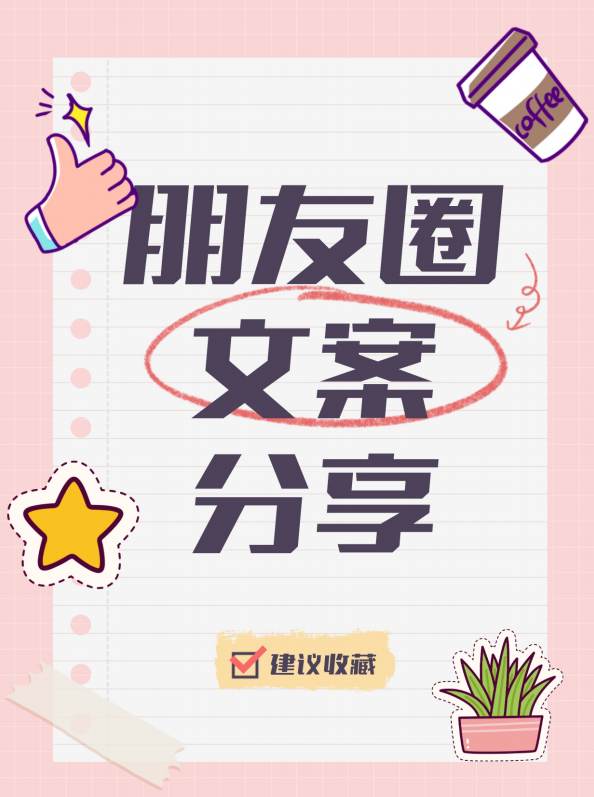
高手庆科冷酷体 大黑
Master-ZqklengkuGB Bold
该字体是一款宽扁的直线黑体,整体硬朗倾斜,中宫略大,布白均匀,重心统一。笔画设计无过多装饰,笔形简约,横细竖粗,笔画断开,笔画切割的起笔处内收更显视觉醒目,笔画折笔处下部分加入切口特点,视觉统一,钩笔画收笔处运用斜切处理,整体倾斜约为5度,视觉秩序感强烈。沿袭中文的设计特点,西文符号以直线为主,加入切角和倾斜的处理,西文风格和中文搭配风格更为统一。